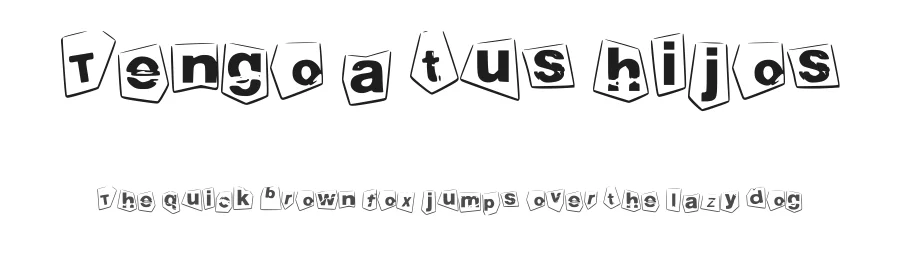
About Square Kids Font
Es una fuente creada para dar la ilusión de que es un dado didactico, creado para un logo de una guarderia
It is a font created to give the illusion that it is a dice didactic, a logo created for a nursery